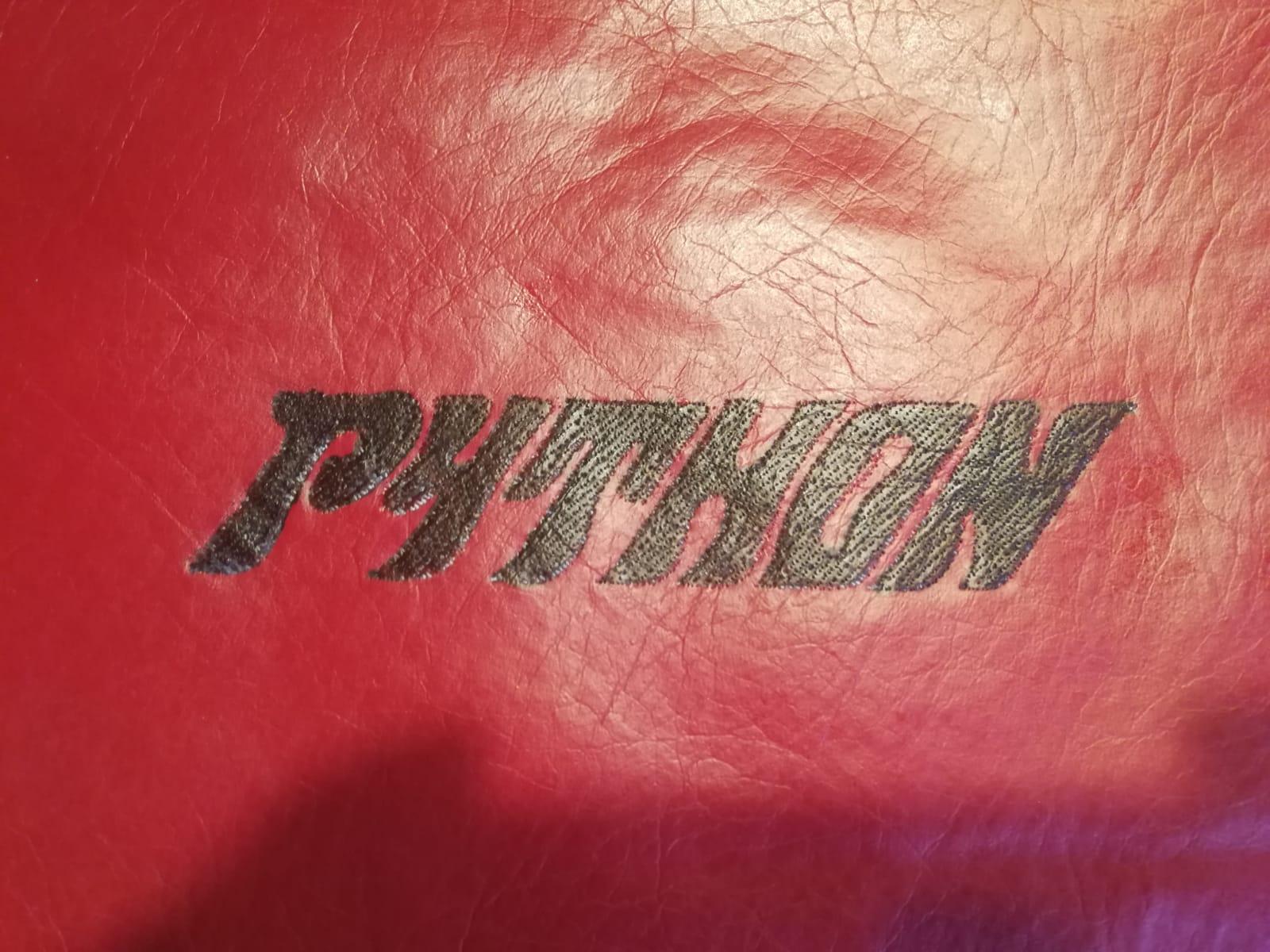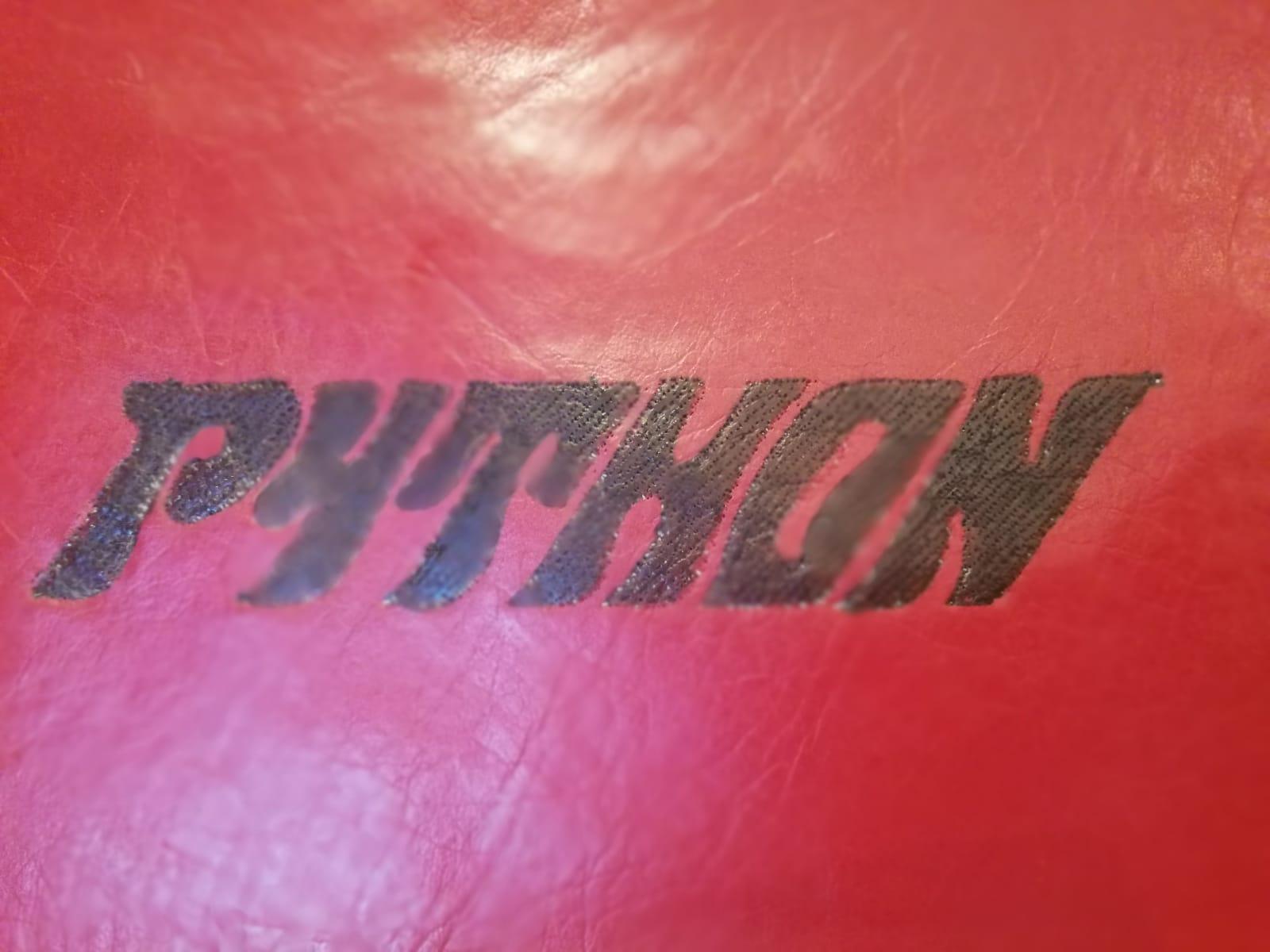
Schriftzug Python (Lederbezug Motorrad)
Hallo, hat jemand schonmal diesen Schriftzug gesehen bzw. weiß, um welche Schriftart es sich dabei handelt?
Der Schriftzug befindet sich auf nem Lederbezug eines ~20 Jahre alten Motorrades
Könnte eine Reminiszenz an den Rudge-Python-Motor sein, der in den 1930er-Jahren u.a. in Zündapp-Motorrädern verbaut wurde. Der Stil des Logos käme zeitlich hin … ob dem überhaupt eine Schrift zugrunde liegt?